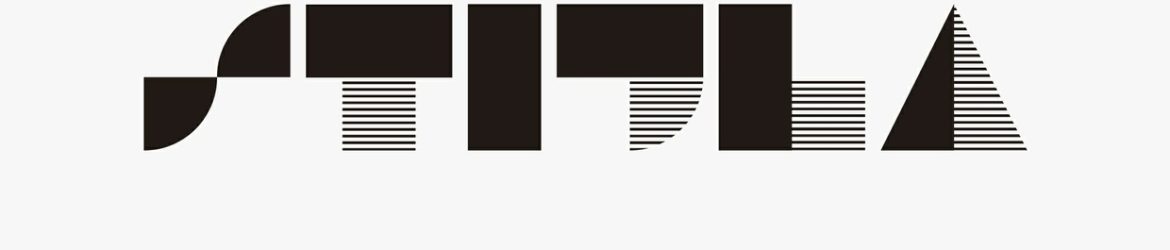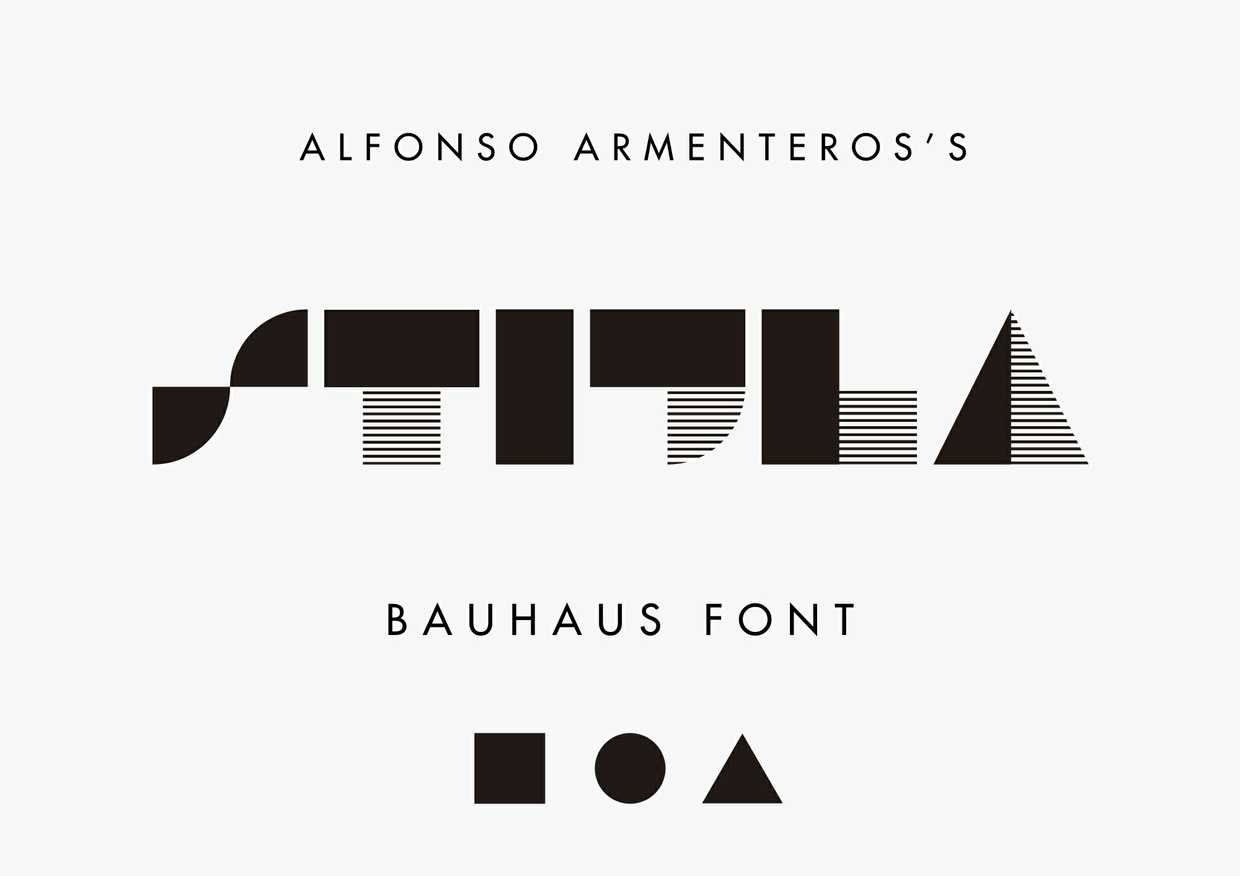
STIJLA Bauhaus-like Font
A fonte STIJLA é uma bela escolha para designers que buscam uma tipografia com um toque de estilo minimalista e artístico. Introduzida por Alfonso Armenteros Parras, a STIJLA™ tem o seu DNA nas linhas puras da Bauhaus e na concepção estética do De Stijl, inspirando-se ainda nos teorizadores da Gestalt. Este conjunto de 147 glyphs oferece uma liberdade criativa perfeita para textos em destaque que precisam de um toque único. A STIJLA™ é ideal como fonte de exibição, dando ao seu design um toque diferenciado e inovador sem comprometer a legibilidade. E assim, a STIJLA™ permite-lhe experimentar o espírito puramente artístico da Bauhaus em uma tipografia que se destaca claramente das demais. Com sua elegância moderna e seu design minimalista, esta fonte é certamente um item de desejo para qualquer designer à procura de uma fonte única e inovadora. Não perca tempo: descubra por si mesmo qual lugar a STIJLA™ pode ocupar em seu próximo projeto visual.